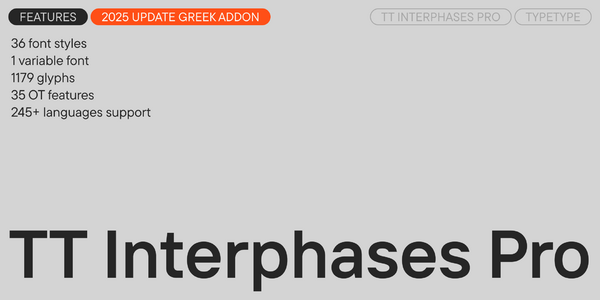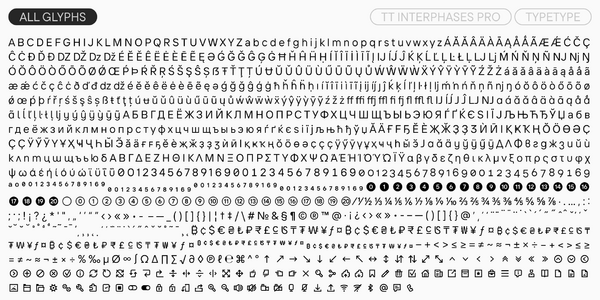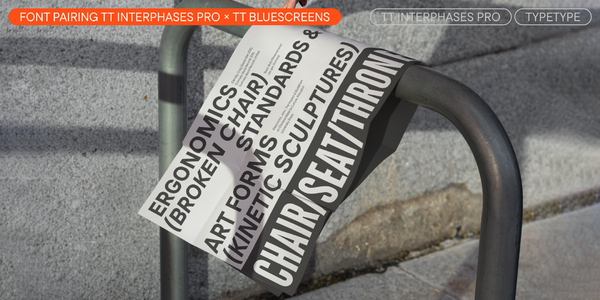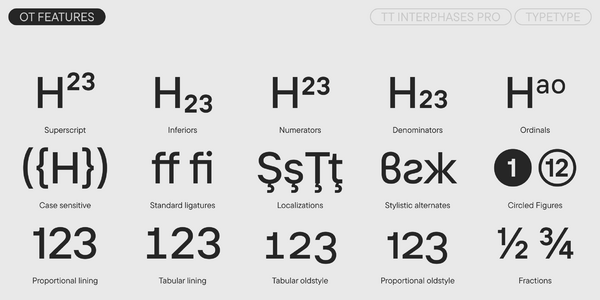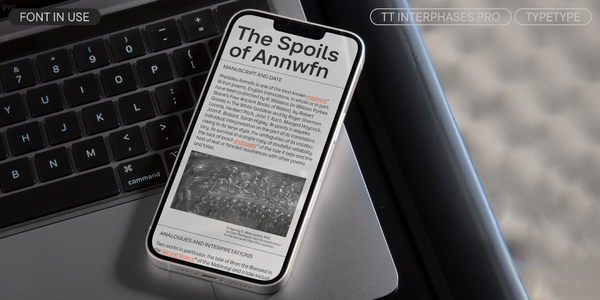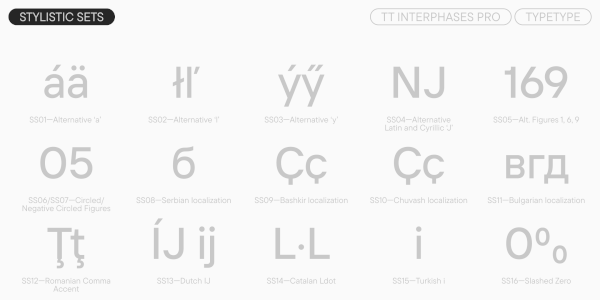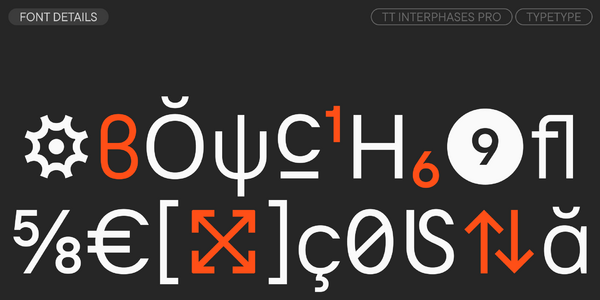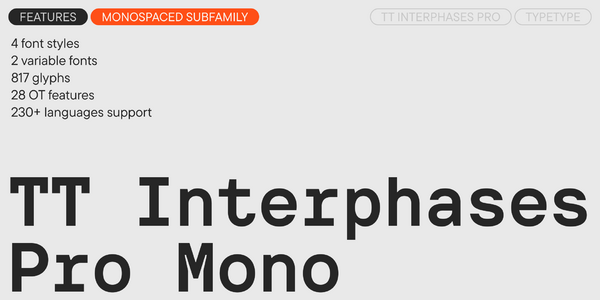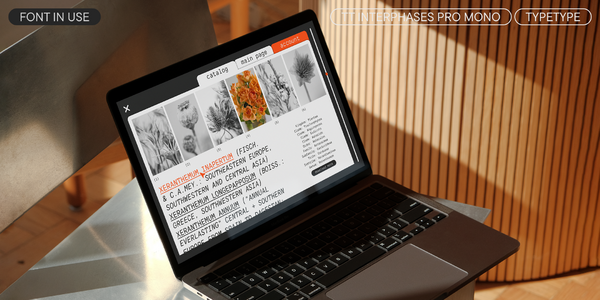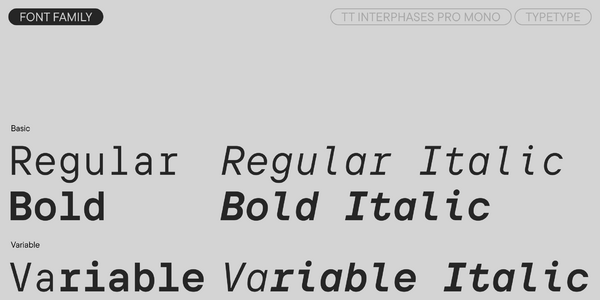
TT Interphases Pro
TT Interphases Pro — ТТ Интерфейзис Про
Произносится «ТТ Интерфейзис Про». «Interphases» — производное слово от interface, в переводе с английского «интерфейс». «Pro» произносится как «про», и является разговорным сокращением слова «профессиональный». Буквы «TT» являются аббревиатурой названия компании.
TT Interphases Pro — неогротеск, созданный специально для работы в интерфейсах. Это стильный, лаконичный и функциональный шрифт, который станет базой для любых платформ.
Универсальная гарнитура для работы с интерфейсами
К основным визуальным особенностям TT Interphases можно отнести открытую апертуру у знаков, равномерное распределение белого и чёрного, а также отличную читаемость. Общая нейтральность рисунка шрифта не лишена элегантности, а все детали шрифта выполнены с математической точностью и любовью. Кроме того, TT Interphases имеет самый современный ручной TrueType хинтинг.
Идеальный шрифт для работы в современных интерфейсах на большинстве известных мобильных и веб-платформах
43 шрифта: 36 шрифтов в базовом семействе, 4 моноширинных и 3 вариативных шрифта.
Встречайте TT Interphases Pro версии 2.100 — теперь с поддержкой греческого языка!
Обновили этот функциональный и удобный интерфейсный шрифт, сделав его ещё совершеннее.
TT Interphases Pro — неогротеск, который создавался специально для работы в интерфейсах. Текст, набранный этим шрифтом, выглядит равномерным благодаря равноширинным пропорциям. Крупный рост строчных знаков улучшает разборчивость шрифта на экране, а нейтральный характер глифов и сквадраченные формы круглых знаков позволяют ему оставаться читаемым даже в маленьком кегле. Плавные формы скруглений повторяются во всех элементах: благодаря им большие массивы текста читаются легко и приятно. А закрытые апертуры делают шрифт современным и узнаваемым.
Характер у TT Interphases Pro нейтральный, при этом эстетичный. Основное подсемейство станет идеальной базой для любых проектов. Подсемейство TT Interphases Pro Mono с интересными формами глифов и единым размером кегельных площадок выглядит более ярко и подойдет не только для использования в кодинге, но и для создания дизайнерских продуктов. А с помощью узкой версии Condensed можно сделать блок текста более компактным.
Особое внимание мы уделили вариативной версии шрифта: в ней можно менять толщину штрихов, ширину и угол наклона знаков. От Thin до Black, от Condensed до Normal, от 0 до 11 градусов — настраивайте шрифт так, как вам необходимо! Кроме того, в обновленную версию мы добавили два вариативных шрифта в подсемейство Mono — они меняются по оси жирности.
В обновленной версии появилась поддержка греческого и других языков, обновились кернинг и хинтинг, а также значительно расширился кассовый состав. В частности, появились знаки валют сум, сом, тугрик во всех регистрах, минускульные пропорциональные и минускульные табулярные знаки валют и минускульные математические знаки.